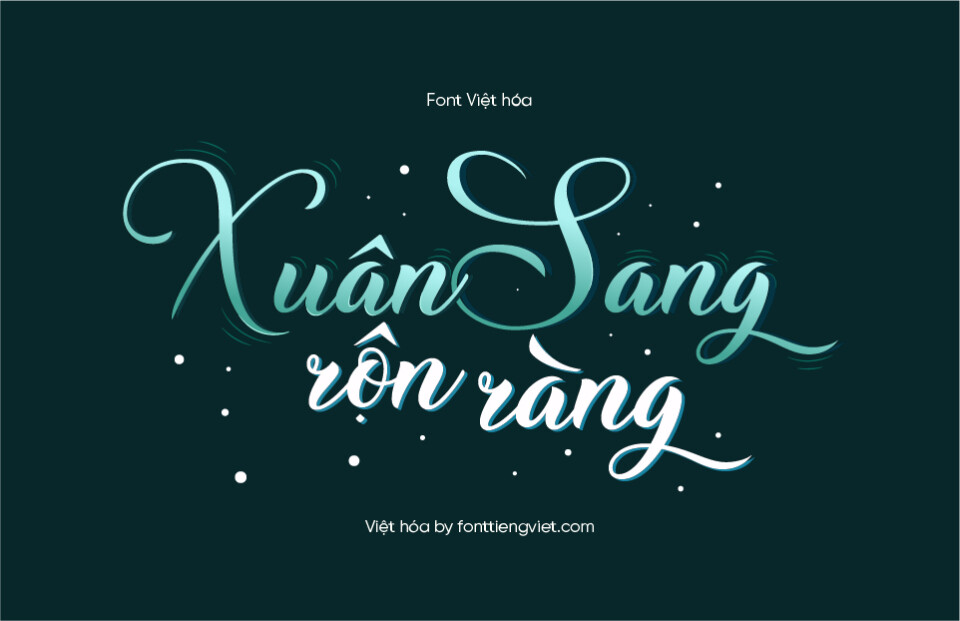
Font Việt hóa 1FTV VIP Christmas Wish Calligraphy – Tết Chào Đón Năm Mới
Giới thiệu bộ Font Việt hóa 1FTV VIP Christmas Wish Calligraphy – Tết
Trong thế giới thiết kế đồ họa, việc tìm kiếm một bộ Font Chữ đẹp mắt để truyền tải thông điệp yêu thương là vô cùng quan trọng. Font Việt hóa 1FTV VIP Christmas Wish Calligraphy – Tết chính là giải pháp hoàn hảo cho những ai đang tìm kiếm sự tinh tế và sang trọng. Với những đường nét uốn lượn uyển chuyển, bộ font này mang đến hơi thở ấm áp của mùa lễ Giáng sinh và sự hân hoan của ngày Tết cổ truyền Việt Nam. Đây là lựa chọn lý tưởng cho các em học sinh và thầy cô giáo muốn tạo ra những tấm thiệp chúc mừng hoặc bài thuyết trình sinh động.
Đặc điểm nổi bật của font chữ nghệ thuật
Sự độc đáo của bộ font nằm ở cấu trúc thư pháp hiện đại nhưng vẫn giữ được nét cổ điển. Các ký tự được chăm chút tỉ mỉ, giúp văn bản trở nên mềm mại và có hồn hơn. Đặc biệt, phiên bản Font Việt hóa 1FTV VIP Christmas Wish Calligraphy – Tết đã được tối ưu hóa hoàn toàn về dấu câu tiếng Việt, đảm bảo không xảy ra lỗi hiển thị khi soạn thảo văn bản chuyên nghiệp.
Ứng dụng thực tế của Font Việt hóa 1FTV VIP Christmas Wish Calligraphy – Tết
Bộ font này không chỉ dành cho các nhà thiết kế chuyên nghiệp mà còn rất gần gũi với môi trường học đường. Các bạn học sinh có thể sử dụng để trang trí báo tường, làm tiêu đề cho các bài tập sáng tạo hoặc thiết kế voucher lì xì cho lớp. Sự kết hợp giữa phong cách Calligraphy và chủ đề Tết giúp mọi ấn phẩm trở nên ấn tượng và thu hút người xem ngay từ cái nhìn đầu tiên. Bạn sẽ dễ dàng tạo ra những tác phẩm nghệ thuật mang đậm dấu ấn cá nhân mà không tốn quá nhiều công sức.
Cách sử dụng font hiệu quả trong thiết kế
Để phát huy tối đa vẻ đẹp của font chữ này, người dùng nên kết hợp với các tông màu rực rỡ như đỏ, vàng hoặc xanh lá cây. Việc điều chỉnh khoảng cách chữ phù hợp sẽ giúp các nét uốn lượn không bị chồng chéo, tạo nên một tổng thể hài hòa và chuyên nghiệp cho toàn bộ bản thiết kế của bạn.
Kết luận về bộ font chữ Tết đặc biệt